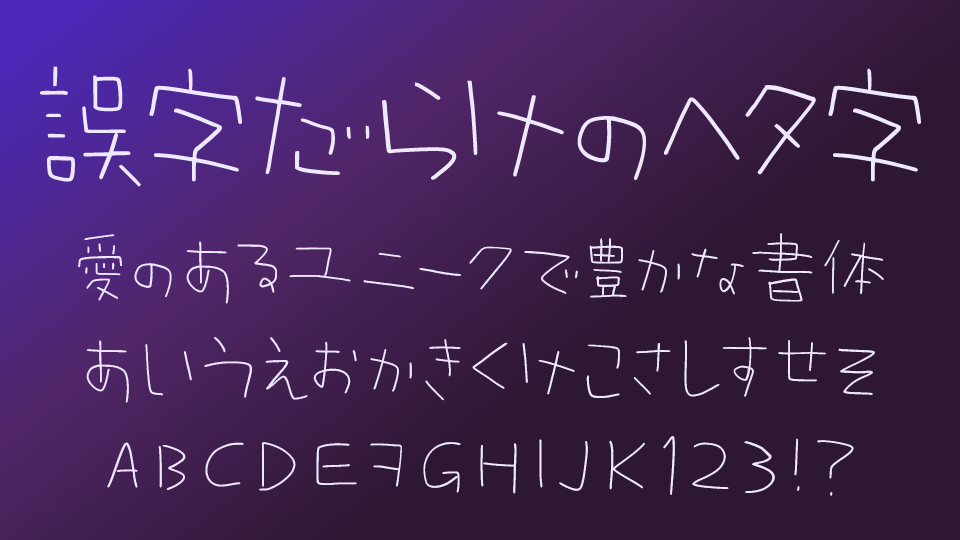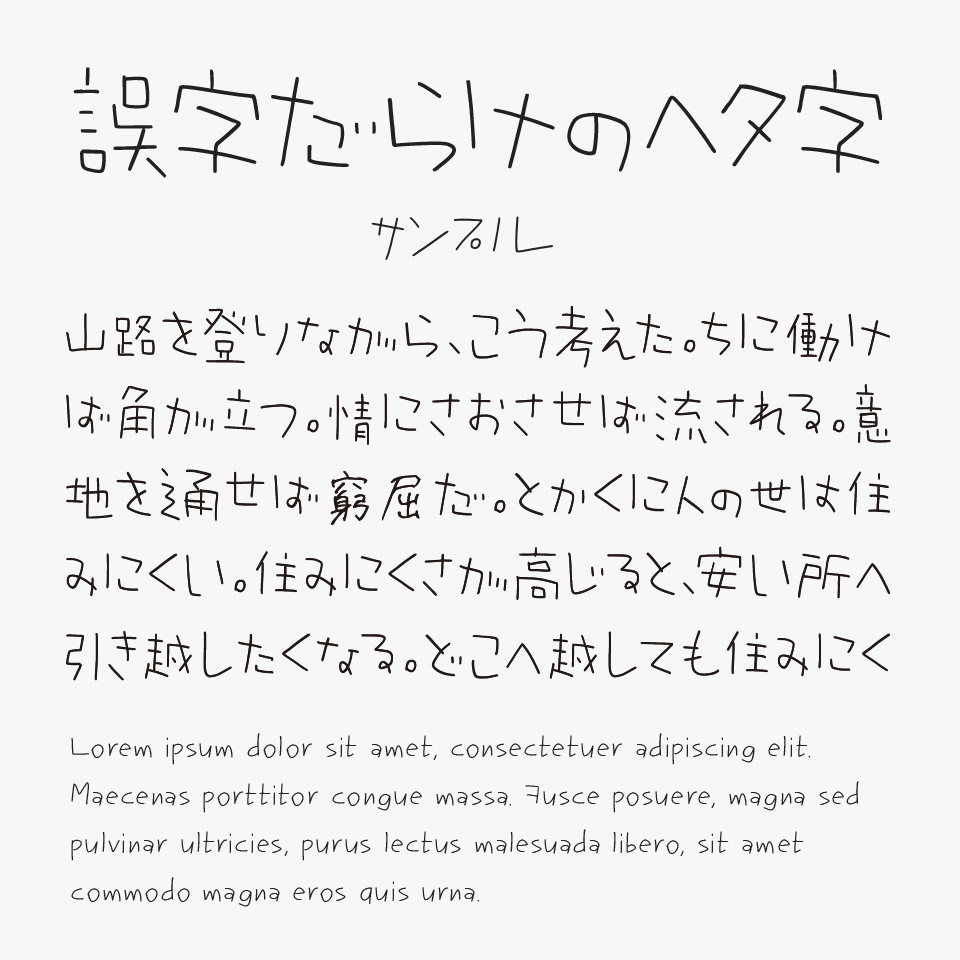
誤字だらけのヘタ字
誤字だらけのヘタ字フォントは、「ひどく字が下手で、漢字が書けない」というユニークなテーマから制作された、急いで書いたメモやノートの落書きをそのままフォント化したような手書きフォントです。
教育漢字(小学校で習う漢字1026字)が収録されていますが、半分以上が誤字と意図的に作られている遊び心あるフォントです。それが整いすぎていない素朴な表情が愛嬌があり可愛らしいです。
真面目に書こうとしているのに、どこか不器用さが見え隠れする絶妙なバランスがあり、手書きならではの人間味や温かさを感じることができます。計算されたデザインでは出せない、リアルな筆跡の空気感がしっかり表現されています。
SNS投稿や日記風デザイン、手紙、漫画の吹き出しなどに使うと、親近感のあるやわらかな雰囲気を演出にぴったりです。肩の力が抜けた、脱力感や自然体のコミュニケーションにおすすめなフォントとなっています。
誤字だらけのヘタ字フォントを、ほかの脱力感を感じる手書きフォントと比較してみると、“時折誤字が混ざっていることで本当に誰かが急いで書いたような不器用さ”が特に魅力のフォントです。
比較フォントは、「きろ字」「みちます」「全員集合!ポップ体」「きずだらけのぎゃーてー」「ひょうきんな!?ポップ体」と使用していますが、どれも独自性のある筆文字風あるフォントなので、ぜひあわせてチェックしてみてください。
収録文字は、漢字(小学校で習う漢字1026字)・ひらがな・カタカナ・アルファベット・数字・記号が収録されています。